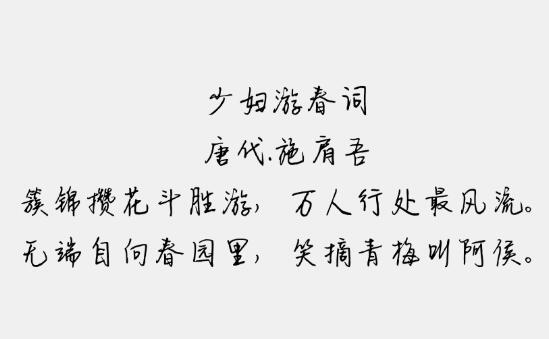
山川星河皆是你是一款十分漂亮的中文字体,同时也是由文道字库倾情发布的作品,字体的距离、菱角、曲线、笔画、颜色都设计的非常合理,适应于报纸和杂志和书籍中常用字体海报、个性促进品牌标志设计、字体设计、文本装潢、信息展示、篆刻制模英文、数据制作、装潢设计、视觉设计、字帖等一切合法应用场景,有喜欢的朋友可免费下载收藏。